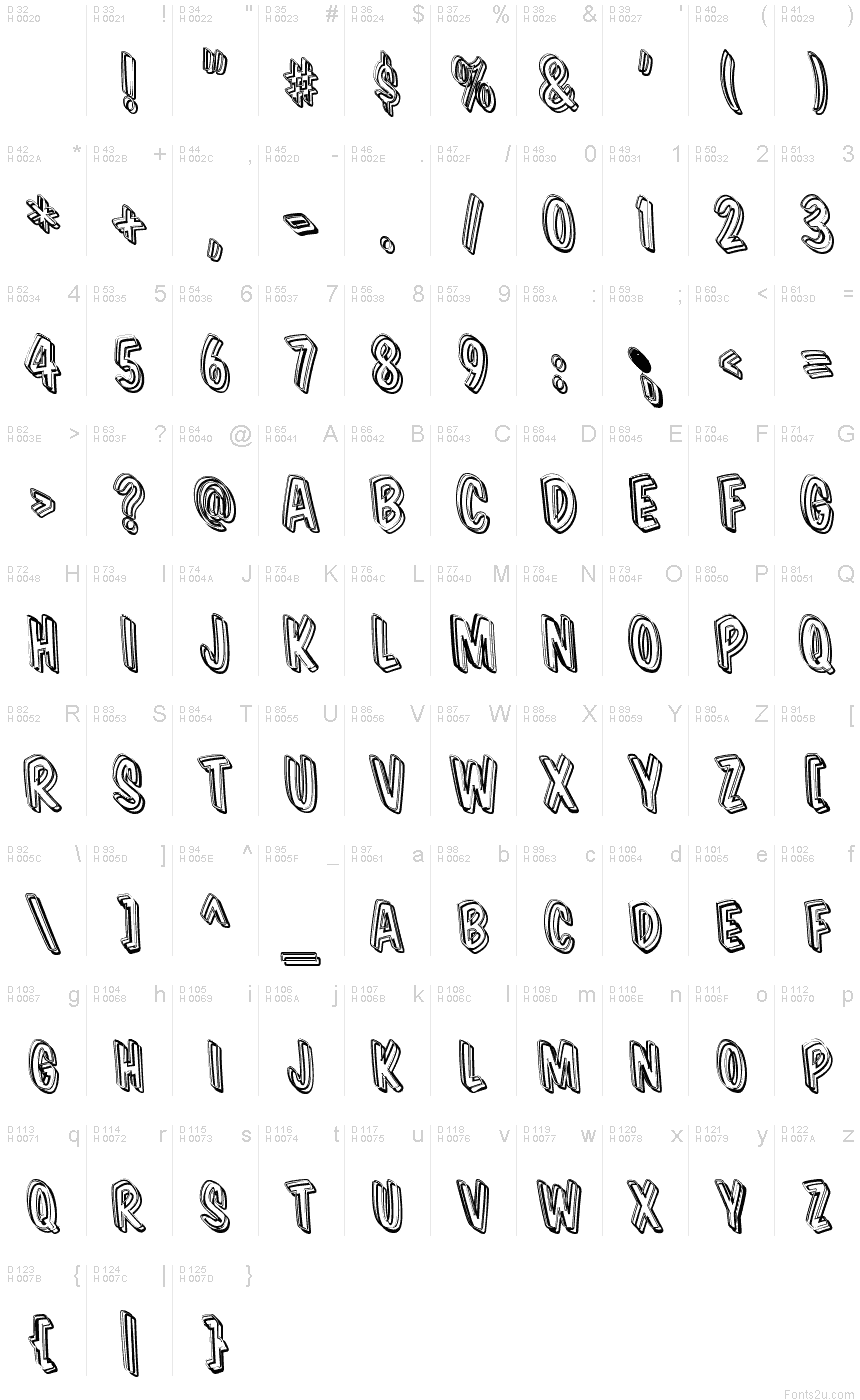
VTC Super Market Sale ODS, di VTC Vigilante Typeface Corporation, è un font display gratuito in stile retro, dotato del fascino chiassoso dei cartelli dei supermercati scritti a mano. Le maiuscole puntano su contorni spessi, angoli arrotondati e un ritmo vivace che sembra incollato sulla vetrina di un negozio, mentre il doppio tratto conferisce alle lettere l'aspetto tipico dei cartellini delle offerte.
Si adatta perfettamente a titoli di volantini, grafiche per vetrine, promozioni su coupon, inviti a feste e poster in cui si desidera un font gratuito, allegro, d'impatto e un po' fatto in casa. Usalo per testi brevi, prezzi in evidenza o iniziali in stile monogramma quando vuoi catturare quell'energia da vecchia bottega, senza scivolare in uno stile tipografico troppo formale.